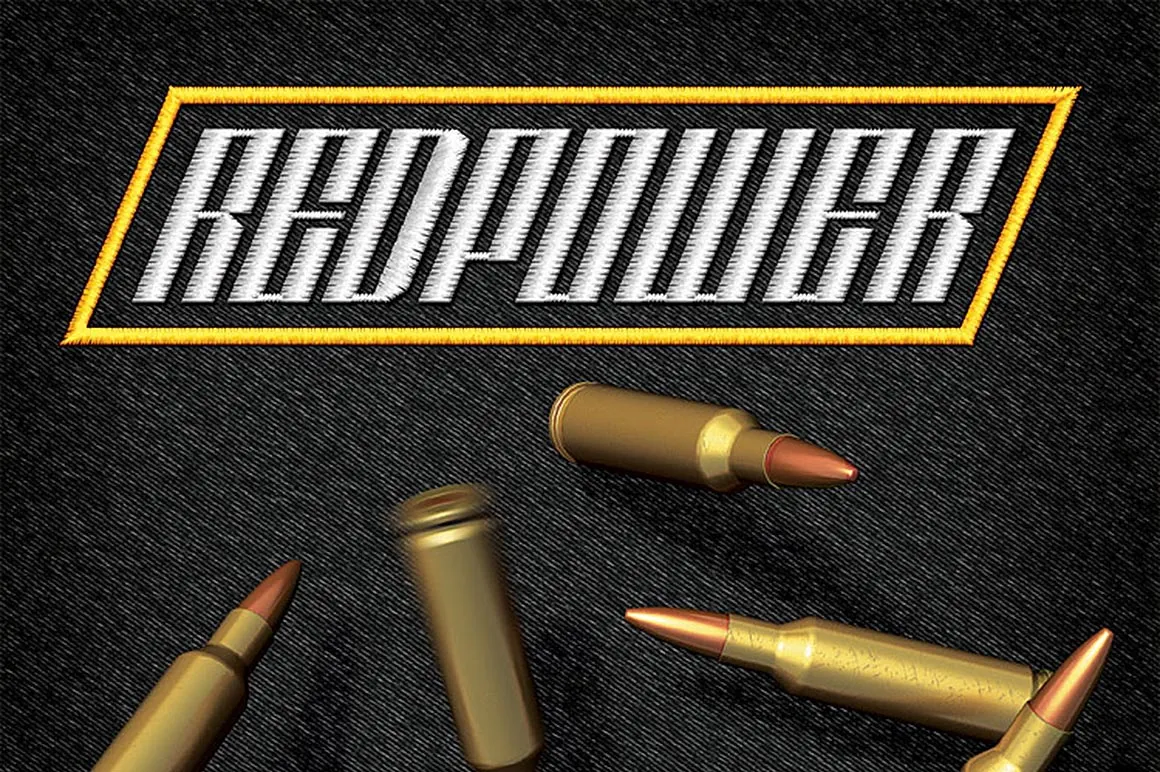
A fonte Redpower Font é uma elegante escolha para designers inovadores no universo do design gráfico. Desenvolvida pelo designer Hamilton, esta fonte sólida e moderna é perfeita para novas propostas criativas que buscam um ar futurista sem perder sua simplicidade única. Sua aparência despojada e clean complementará qualquer projeto digital ou impresso com mestria. Ideal para design de sites, editoriais digitais e até mesmo para criar uma identidade visual original, esta fonte tem o poder de transformar qualquer marca em destaque na web. Certifique-se de experimentá-la no próximo projeto que estiver desenvolvendo!